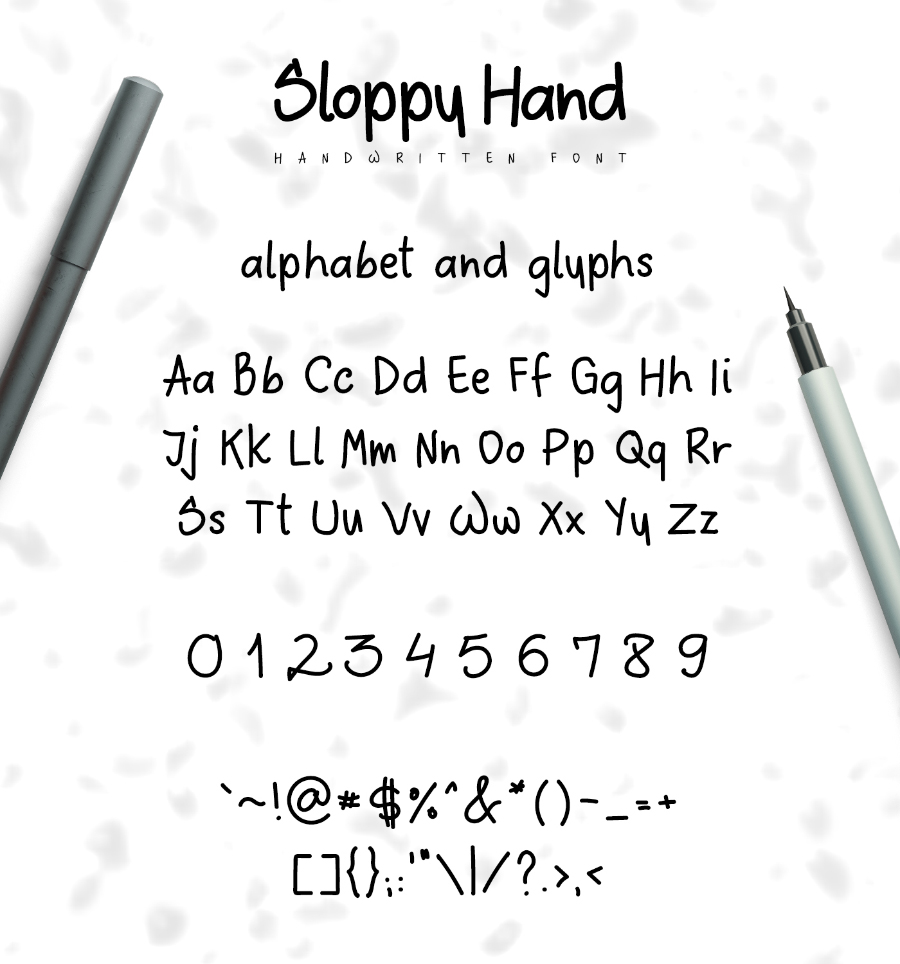
Sloppy Hand Free Typeface
时间新的免费赠品!看看这个手写字体来自Design A Lot。可以用于标志设计,演示文稿,标题的松散的免提字体。与标语和任何有趣的设计,你可能正在努力的伟大作品。字体背后的想法是保持它尽可能真实,所有的不完美之处!你可以看到它的粗糙和马虎 - 它的名字,使它看起来真实和熟悉。此外,字体是免费的个人和商业用途!这意味着您可以将其用于个人项目以及您的客户项目!